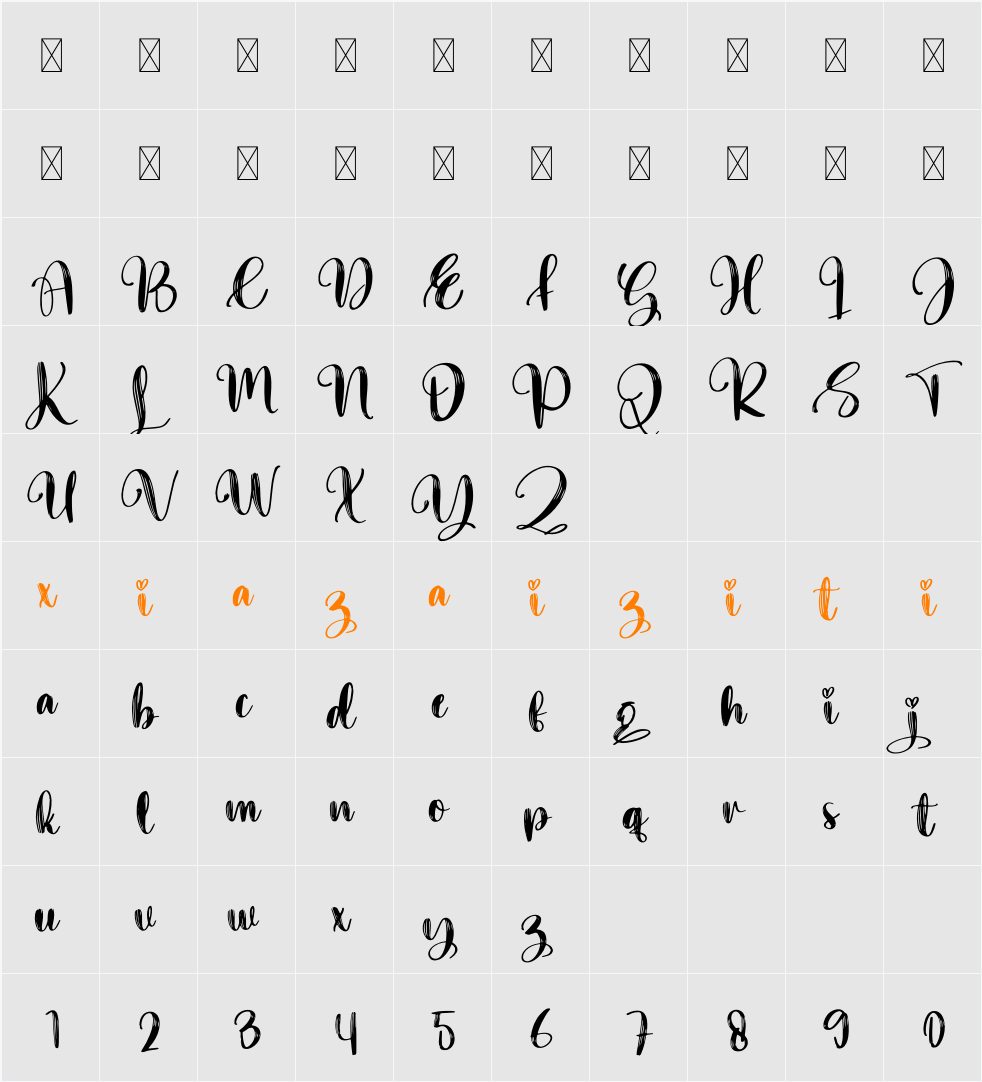
Younger
Younger,这款字体结构工整、笔画清晰,兼顾美观与易读性,适用于标题、正文、海报、包装、LOGO 等多种场景。字形优雅稳定,风格百搭耐看,适配日常排版与创意设计,让文字呈现更舒适、更具质感。Younger一笔一画,皆是细节,以均衡的比例、流畅的线条打造舒适视觉体验,字形端正大气,风格简约现代。无论是商业设计、品牌宣传还是日常排版,都能轻松驾驭,让文字更有格调与力量。Younger字体下载。